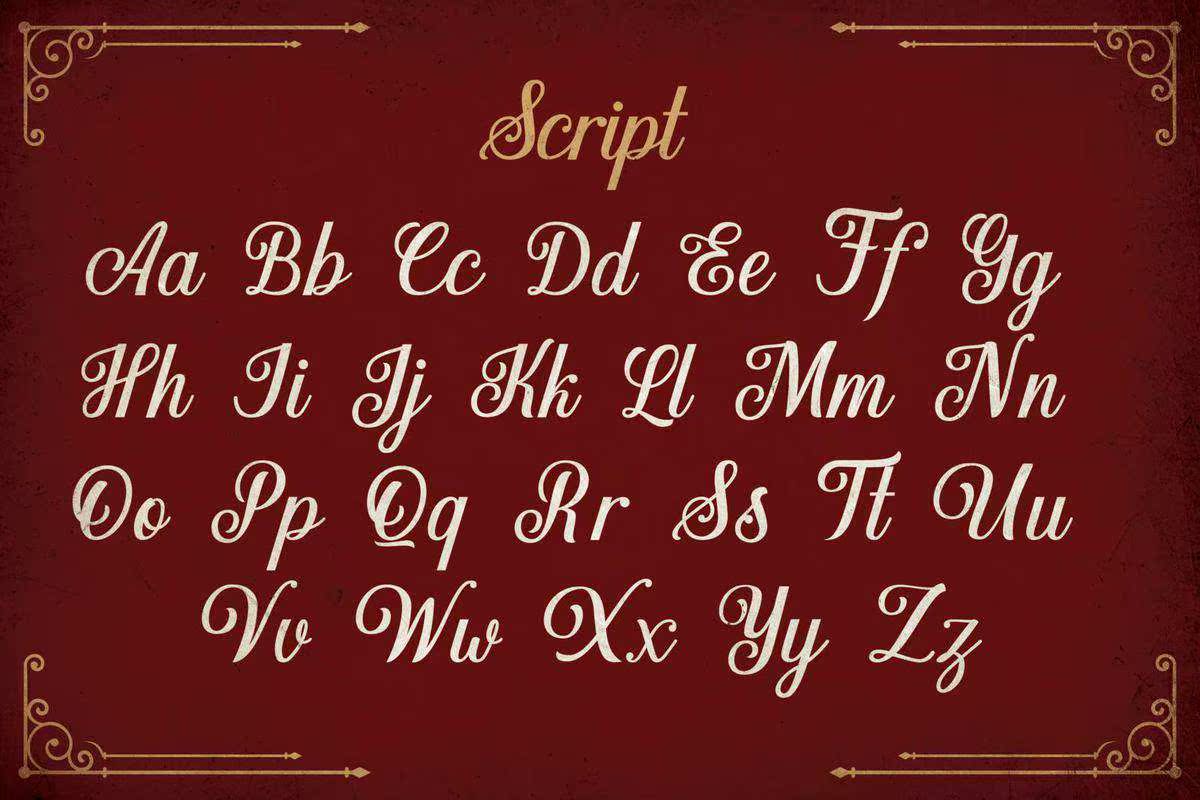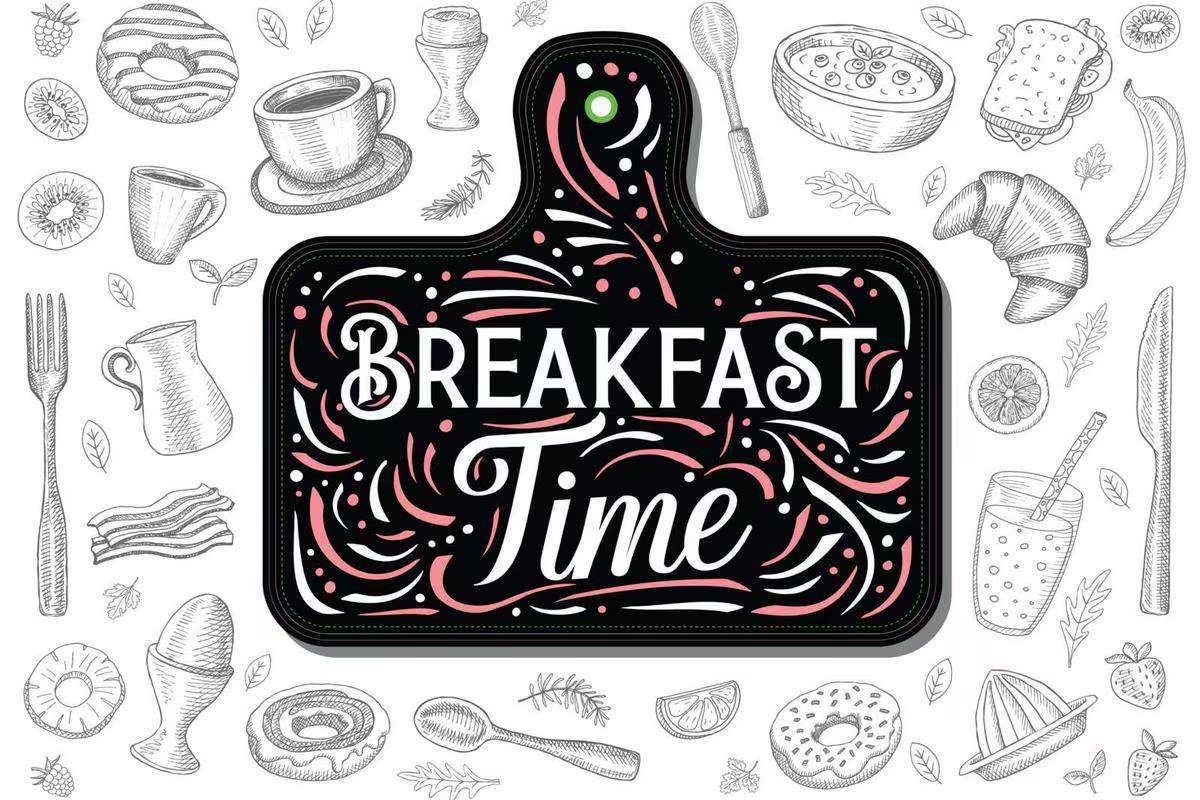
Darktown是Decorativesans and ScriptmadeWithLove,适用于PosterDesign、Logo、Signs和排版。有两种类型的FontScripts和Sans将支持您的项目。同时还有一种可以在插图中看到的文本样式。Darktown是Decorativesans and ScriptmadeWithLove,适用于PosterDesign、Logo和,标志和排版。有两种字体脚本和san将支持您的项目。同时还有一种文本样式,可在插图中查看。